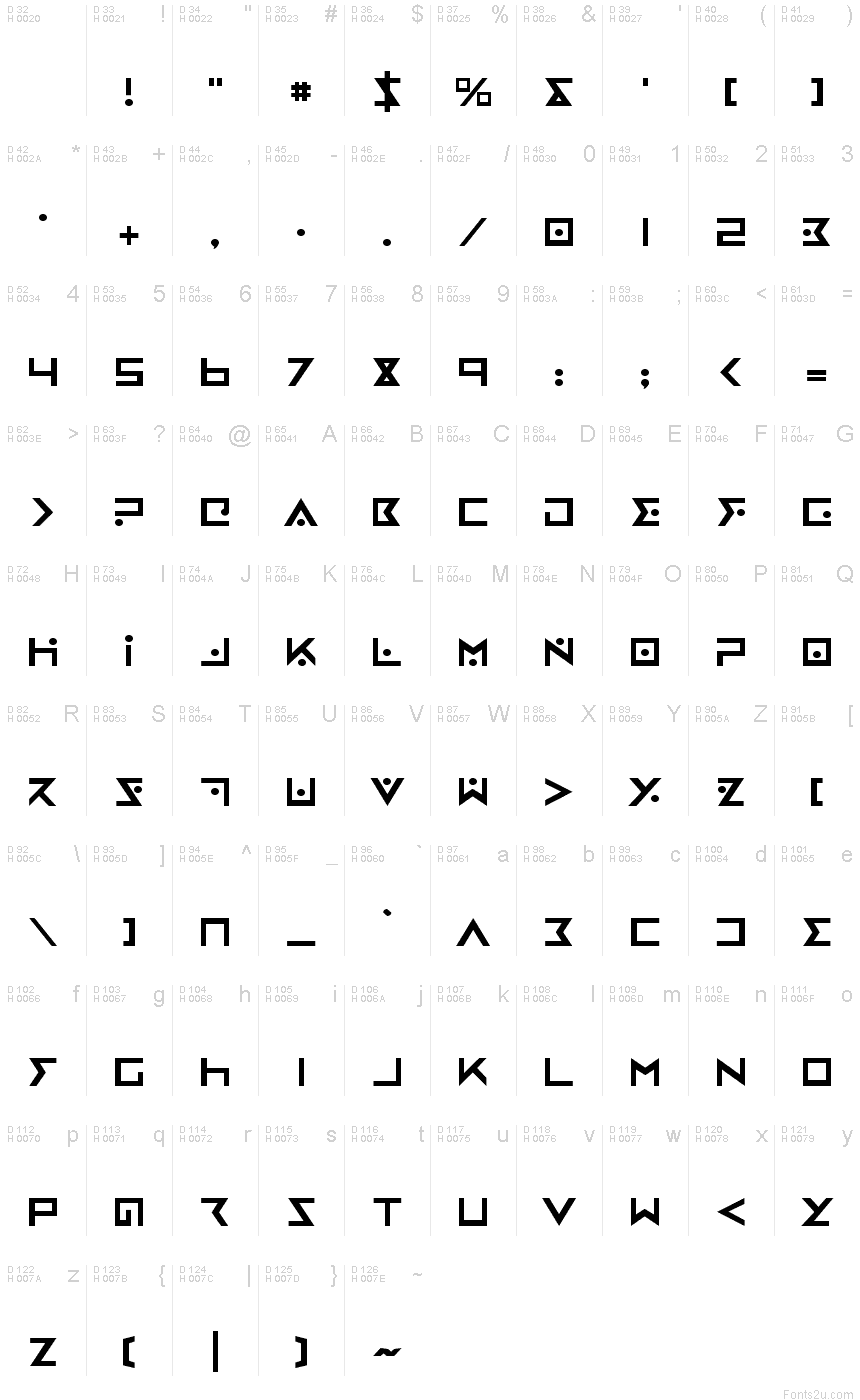
Iron Cobra to darmowy techniczny krój pisma typu display od Iconian Fonts, wyróżniający się surową geometrią i mechanicznym charakterem. Ciężkie, prostokątne formy łączą się z ostrymi, ukośnymi cięciami, a kwadratowe krzywizny i gwałtowne załamania nadają literom surowy, futurystyczny rytm.
Ten darmowy font świetnie sprawdzi się w logo gier, brandingu e-sportowym, plakatach science-fiction, okładkach albumów elektronicznych oraz opakowaniach przemysłowych. Jego odważna, kanciasta konstrukcja sprawdza się również w krótkich nagłówkach i tytułach, gdzie zwarte, techniczne kształty przyciągają wzrok bez potrzeby stosowania dodatkowych ozdobników.
Iron Cobra